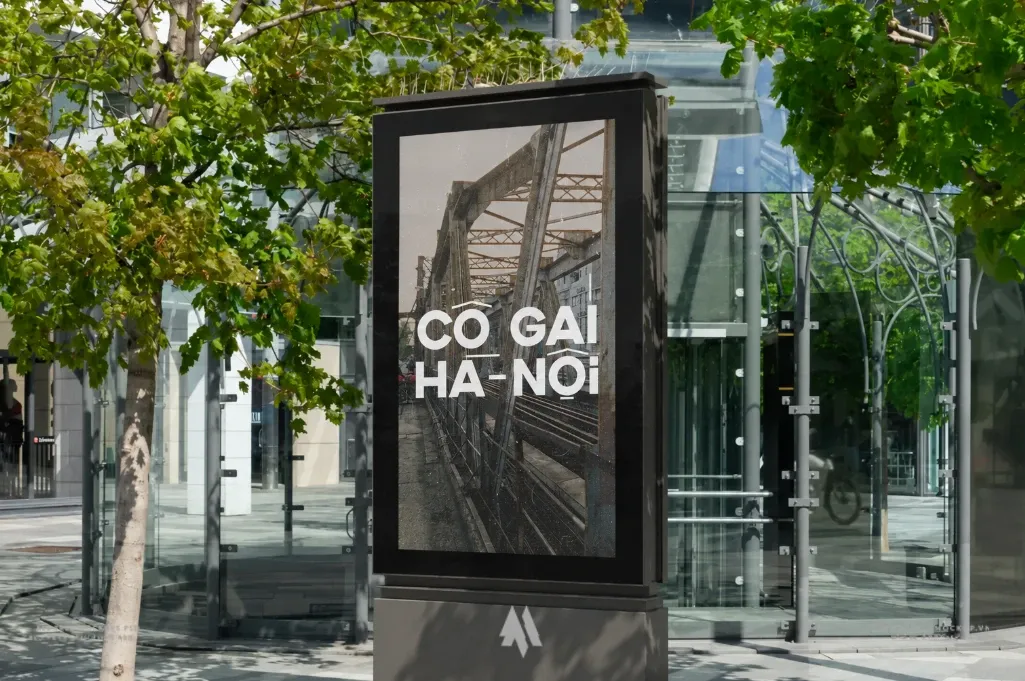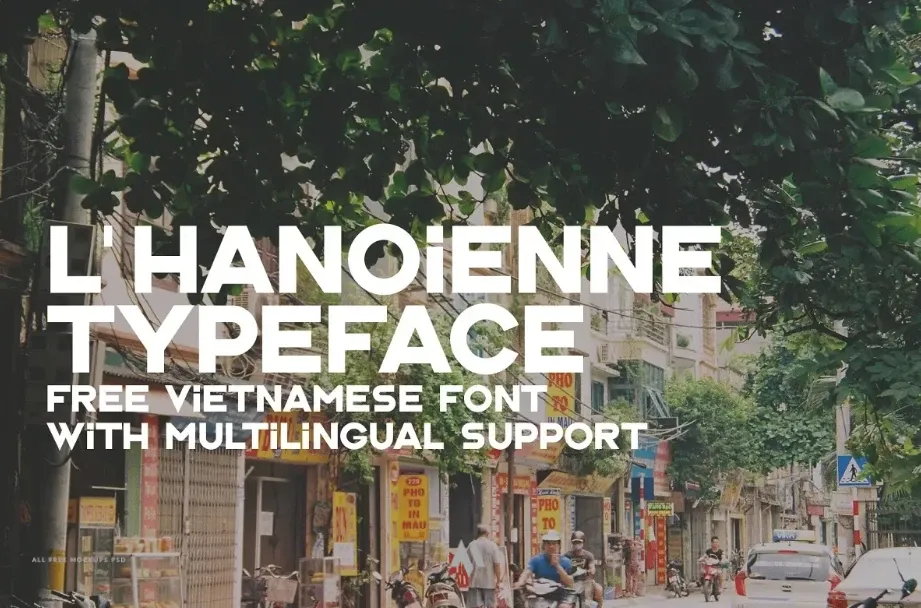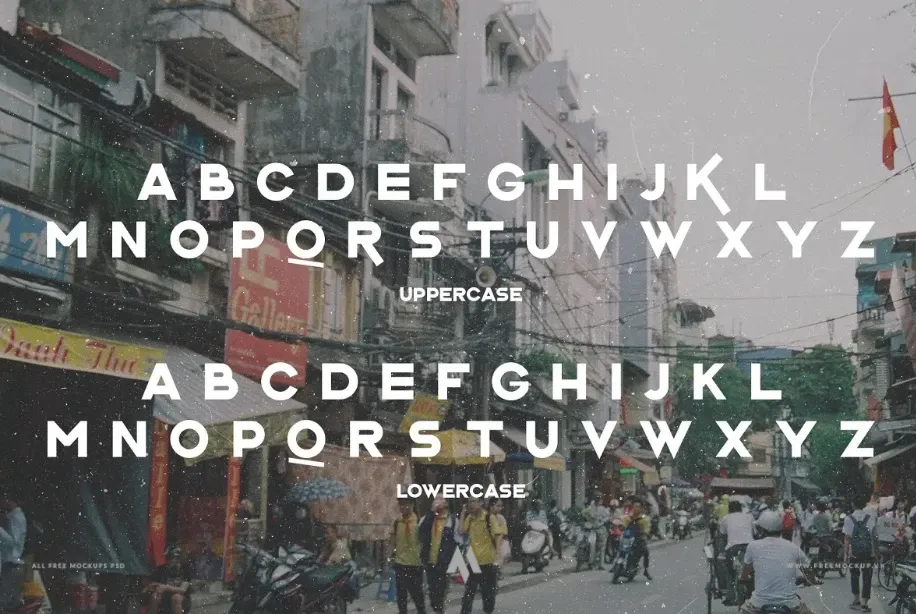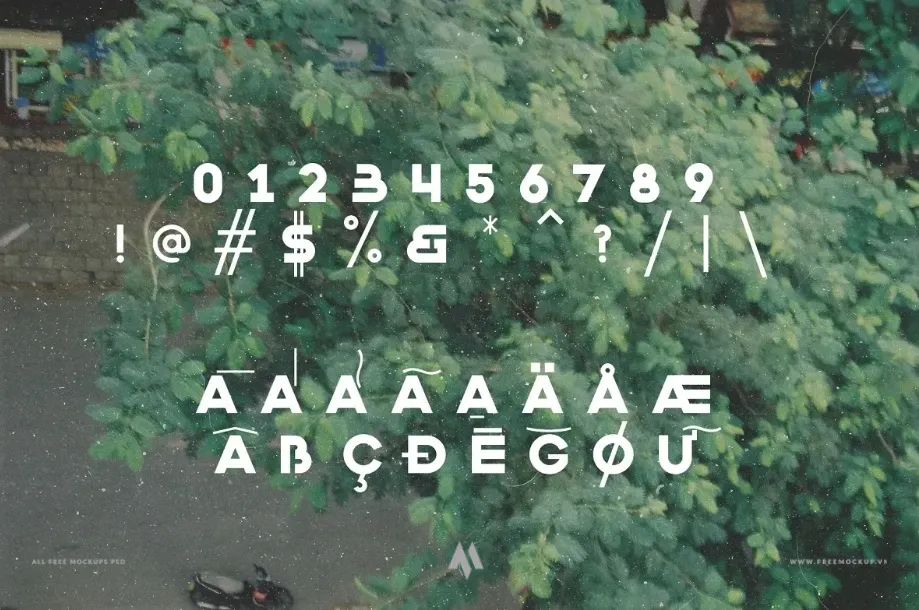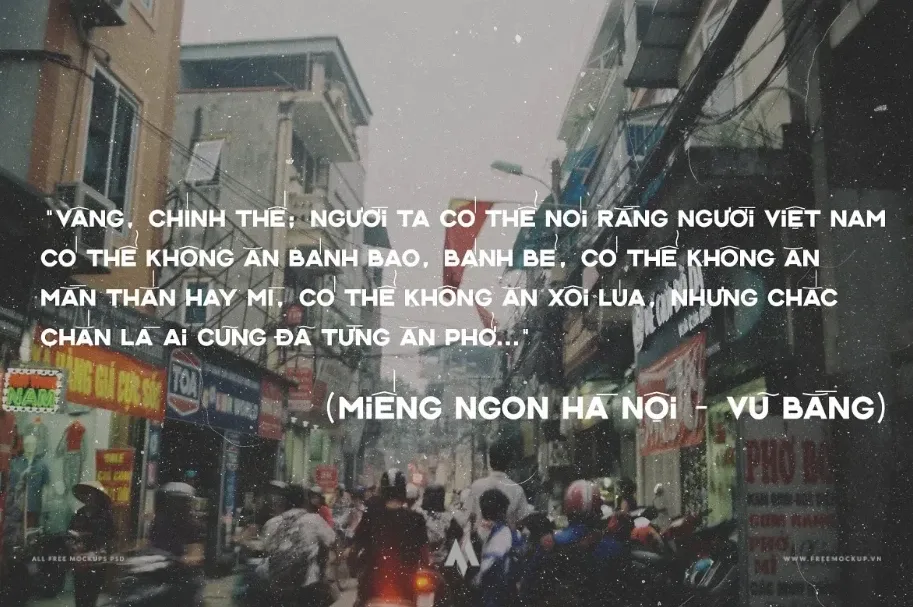
Nếu bạn đang tìm kiếm một bộ typography mang đậm dấu ấn văn hóa, vừa phảng phất nét cổ kính thế kỷ 20 vừa giao thoa tinh thần hiện đại, L’Hanoienne Typeface chính là mảnh ghép hoàn hảo cho các dự án thiết kế retro và văn hóa.
Bản font hỗ trợ trọn vẹn bộ ký tự tiếng Việt có dấu chuẩn xác theo thiết kế gốc của tác giả. Khả năng hiển thị mượt mà trên mọi phần mềm đồ họa: Adobe Photoshop, Illustrator, InDesign, Canva, Figma…